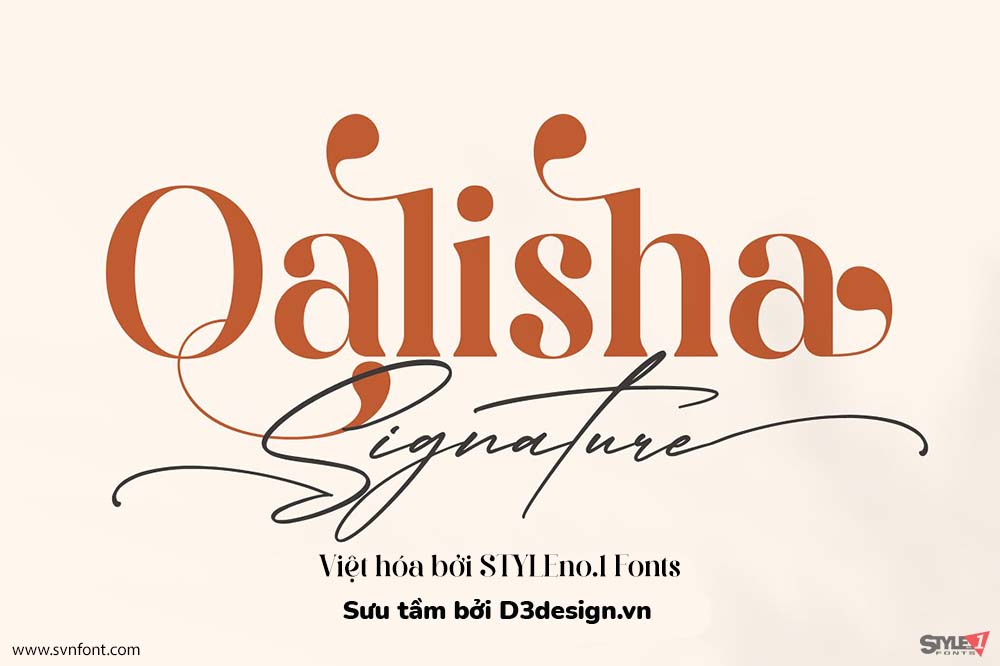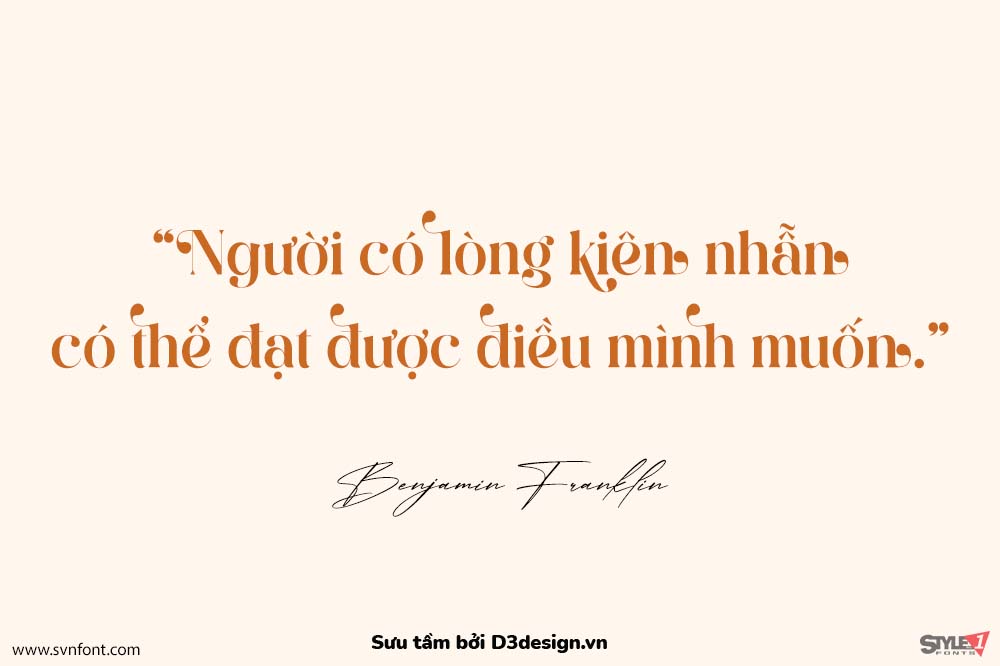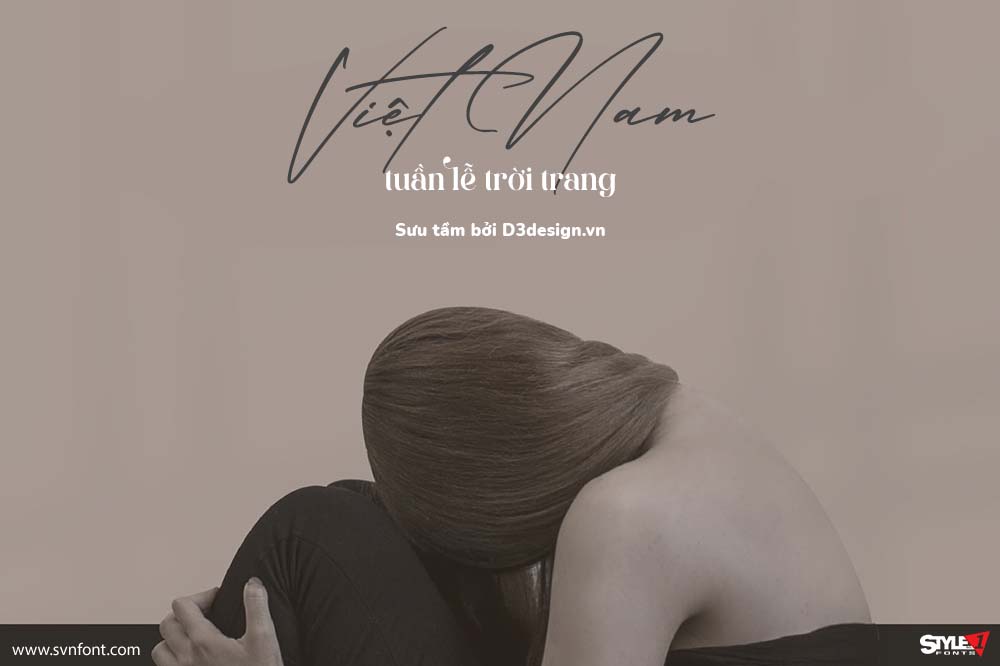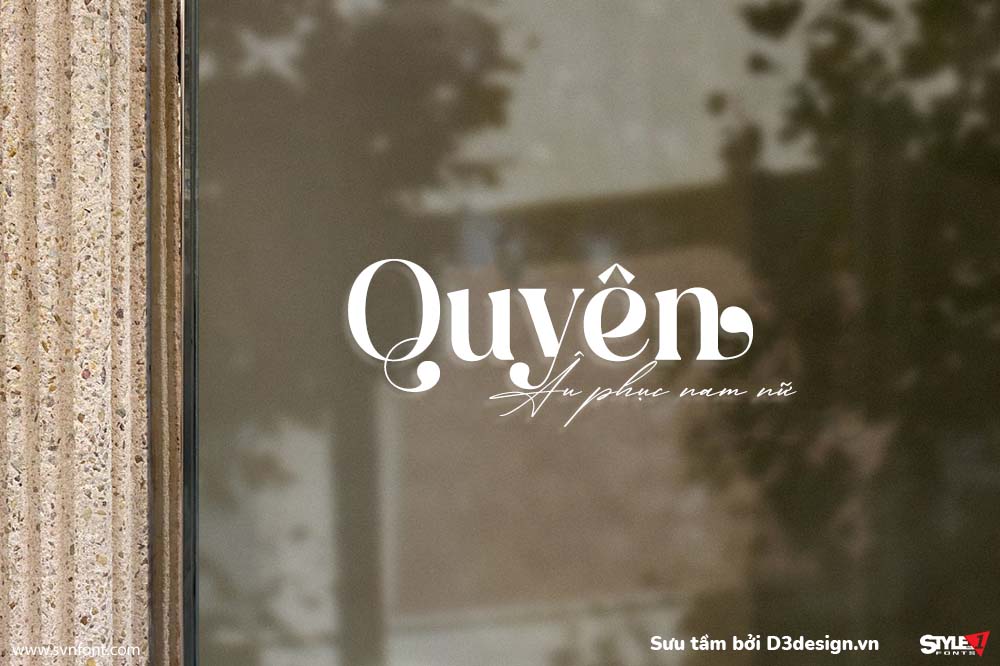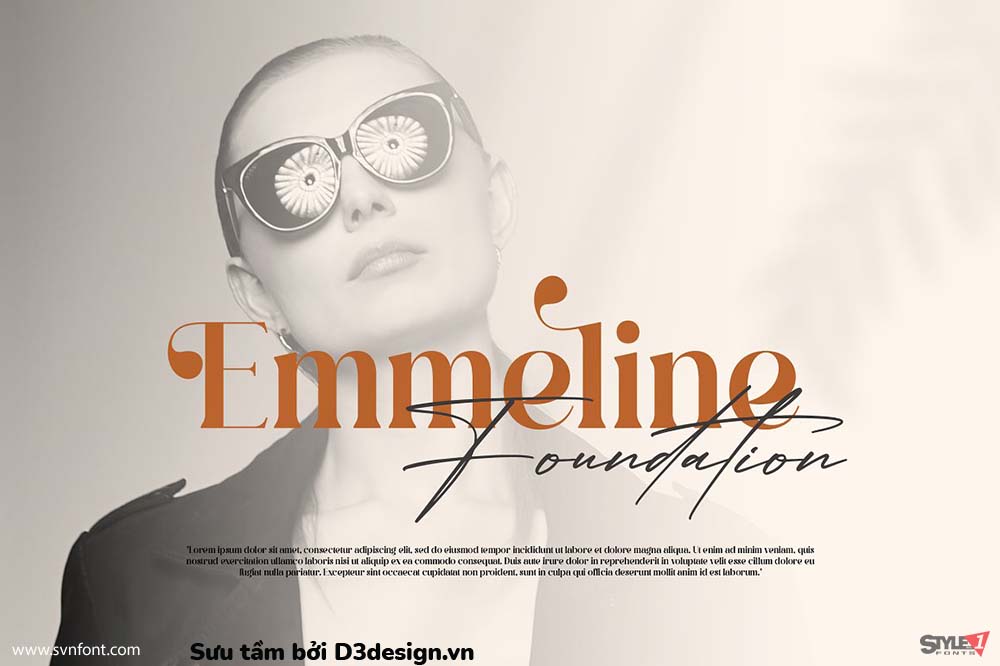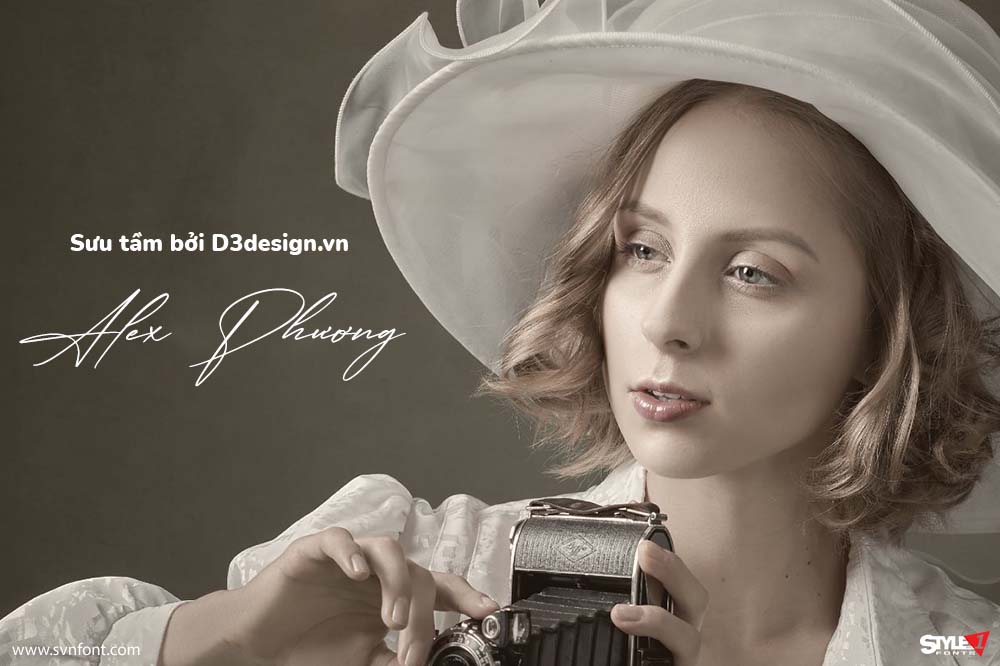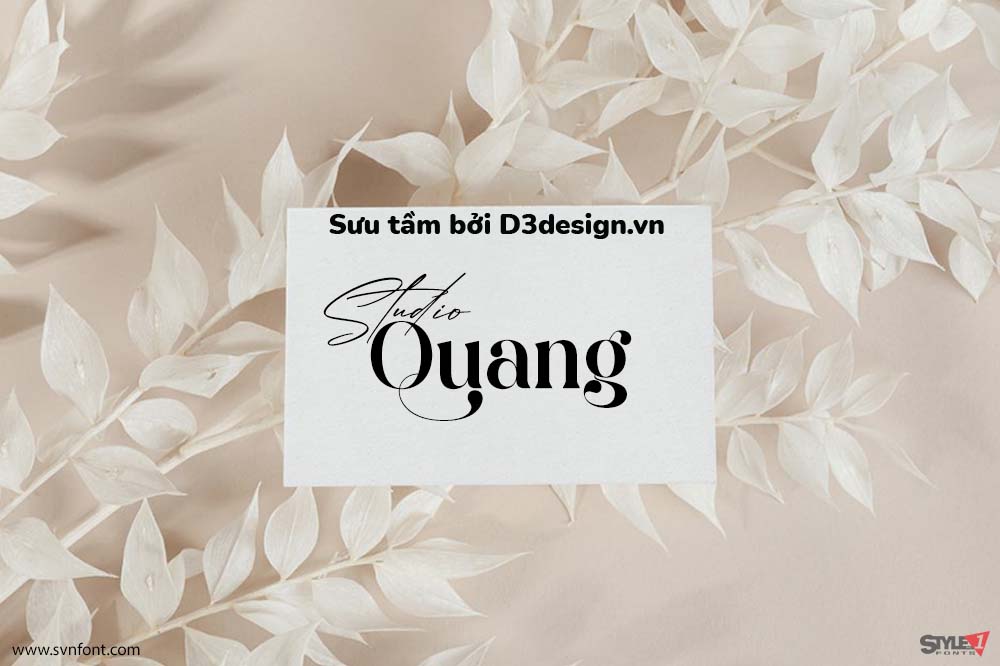
Font Việt Hóa SVN- Qalisha (2 Font) Phong Cách Cổ Điển, Sang Trọng
Qalisha gồm 2 fonts là Serif kiểu đậm cổ điển và Signature kiểu chữ ký, một bộ đôi hoàn hảo cho các thiết kế mới của bạn. Font có hỗ trợ một số ký tự thay thế, mang lại một số kết hợp cho chữ...
Nhà thiết kế: Heru Utama Putra
Nhà phát hành: Storytype Studio
Việt hóa: STYLEno.1 Fonts